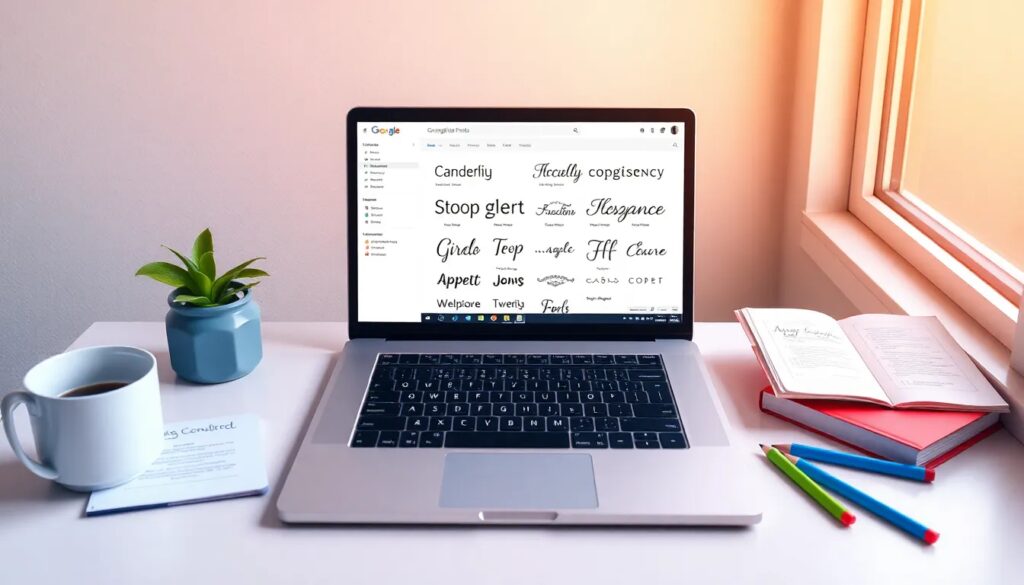
Descarga de Google Fonts
Google Fonts es un recurso invaluable para diseñadores y desarrolladores que buscan fuentes tipográficas gratuitas y de alta calidad. Con más de 600 fuentes disponibles, este servicio no solo permite la descarga, sino que también facilita su integración en sitios web y aplicaciones. En esta guía, exploraremos cómo funciona Google Fonts, los tipos de fuentes que se pueden encontrar y cómo puedes aprovecharlo al máximo en tus proyectos.
¿Cómo funciona Google Fonts?
Google Fonts es una biblioteca de fuentes web de código abierto que permite a los usuarios acceder a una amplia variedad de tipografías. Al ser un proyecto de Google, las fuentes están disponibles para su uso gratuito, lo que las convierte en una opción ideal para proyectos personales y comerciales.
¿Qué tipos de fuentes puedo encontrar en Google Fonts?
Google Fonts alberga una amplia variedad de tipos de fuentes, clasificadas en diferentes categorías. Algunas de las más comunes incluyen:
- Serif: Fuentes con remates en los extremos de las letras, ideales para textos impresos.
- Sans Serif: Fuentes sin remates, perfectas para diseños modernos y limpios.
- Display: Fuentes decorativas que destacan en títulos y encabezados.
- Monospace: Fuentes donde cada carácter ocupa el mismo espacio, útiles para código y programación.
Cada categoría cuenta con múltiples estilos y pesos, permitiendo a los diseñadores elegir la opción que mejor se adapte a su proyecto. Además, Google Fonts es compatible con fuentes HTML, lo que facilita su uso en plataformas de desarrollo web.
¿Cuáles son las fuentes más populares en Google Fonts?
Algunas de las fuentes más populares en Google Fonts han ganado popularidad por su versatilidad y estética. Aquí te presentamos algunas de las más destacadas:
Al aprovechar al máximo Google Fonts, no solo mejorarás la estética de tus proyectos, sino que también aumentarás su funcionalidad y usabilidad. Con la amplia variedad de fuentes disponibles, puedes asegurarte de que tu diseño se destaque y cumpla con los estándares modernos de diseño web.